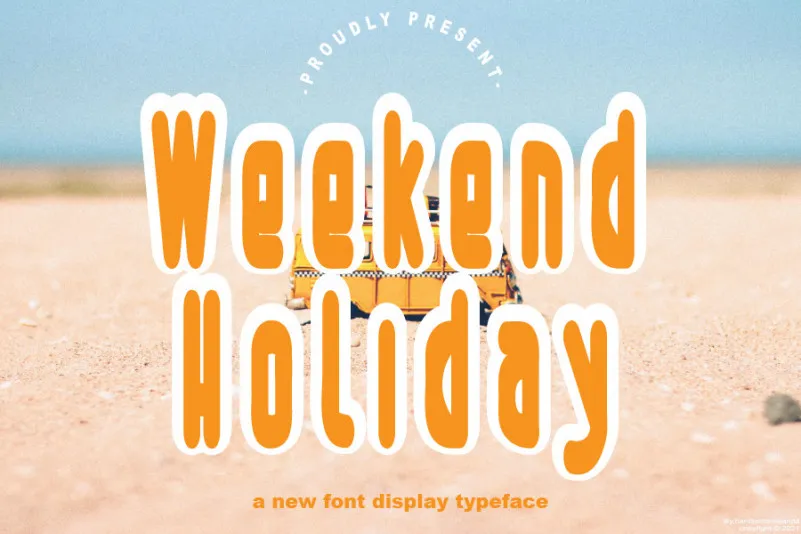
Weekend Holiday Font – Download Grátis
Esta é uma fonte script equilibrada e refinada que transmite sofisticação e elegância. Ela tem alternativas estilizadas e ligaturas que a tornam perfeita para qualquer projeto. Atenção: Fonte Weekend Holiday Display não pode ser usada em propósitos comerciais ou lucrativos sem o consentimento do autor/administrador, sem ser conhecido a usar esta fonte sem consentimento, será punido com uma multa de cinco vezes o valor especificado. Esta font é perfeita para demos (licença demo). Ela transmite sofisticação e elegância, sua estilização única faz desta uma escolha segura e desafiadora para qualquer projeto. Seja você um designer de grafismo profissional ou amador, a Weekly Holiday Font é uma opção ótima para dar um toque especial à sua obra, sem precisar sair da sua fonte padrão. Aproveite!
Designer: handwrittenwanda